バナーやサムネイル、SNS画像などで、パッと目を引く文字を作りたいときにはちょっと個性的なフォントを使うとアクセントとして引き立ててくれます!
でも、こういうフォントは種類がありすぎてどれを使ったらいいのか、そもそもどんなフォントがあるのか分かりづらいですよね…?
ポップなフォントはこんなシチュエーションでおすすめ
特に「とにかく目立たせたい」「大きく印象づけたい」ときに個性的なフォントは力を発揮します!
具体的にはこんなシチュエーションがあげられるかと思います。
- YouTubeやブログのサムネイルのタイトル文字
- SNS投稿や広告画像の見出し
- イベント告知・キャンペーン用のバナー
- 推し活グッズ(うちわ・ネームボード・スローガン)
- 表紙などで一言ドン!と見せたいとき
あかずきんポップ
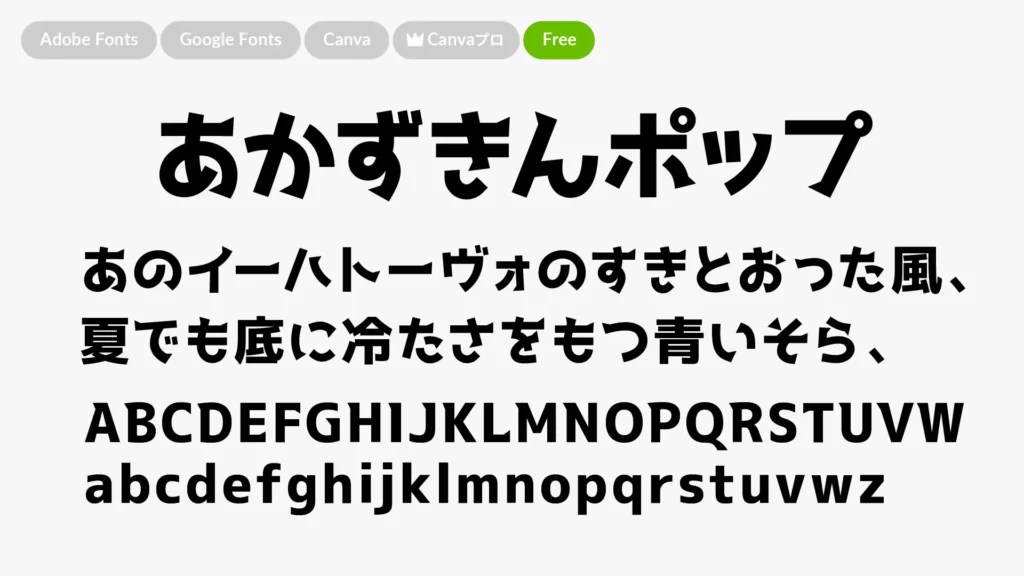
- はねたような先端が特徴の元気でポップなフォント
- 太さがあるのでYoutubeサムネイルなどにも使える◎
ABキリギリス
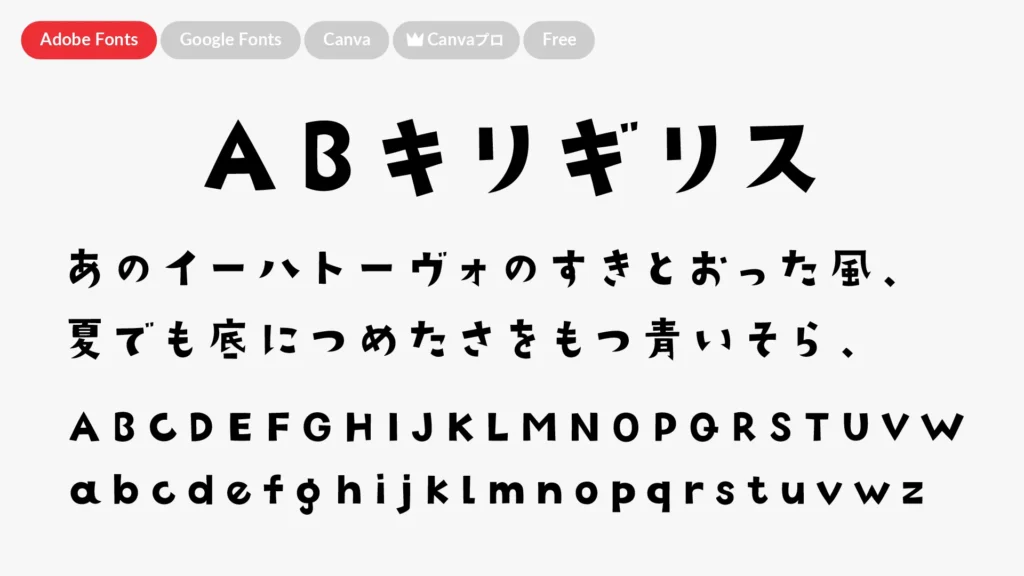
- コロっとしたちいさなフォント
- 切り絵みたいな手作り感溢れるフォルムがかわいい
ABとんぼ
- ちょっと縦に長めなのびのび楽しげな雰囲気をもつフォント
- 太さがあってポップなのでYoutubeサムネイルに使えそう
メガ丸
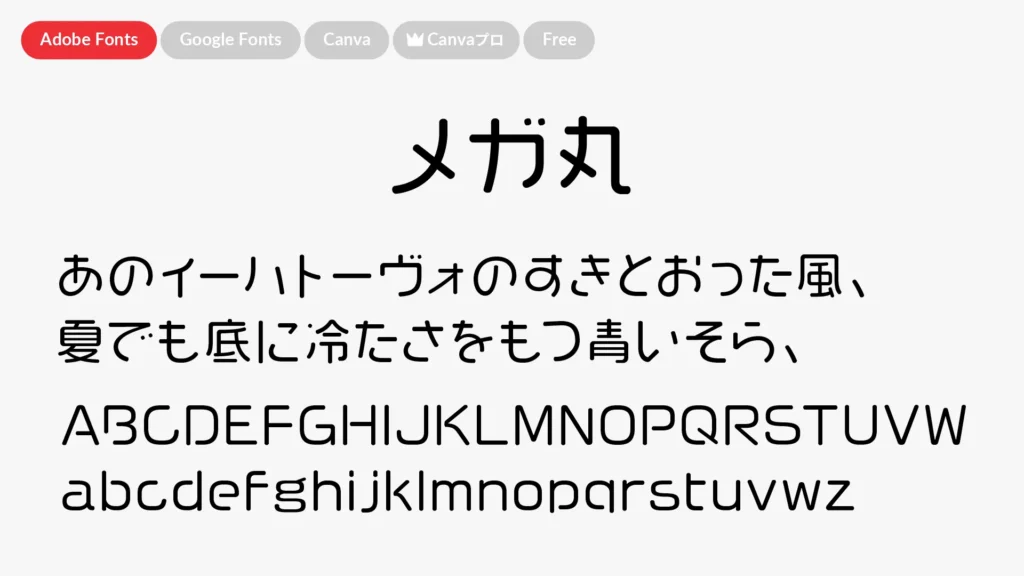
- 大胆な丸みをもつ個性的な丸ゴシック
- ユニークな漢字も多めに収録
バナナスリップ
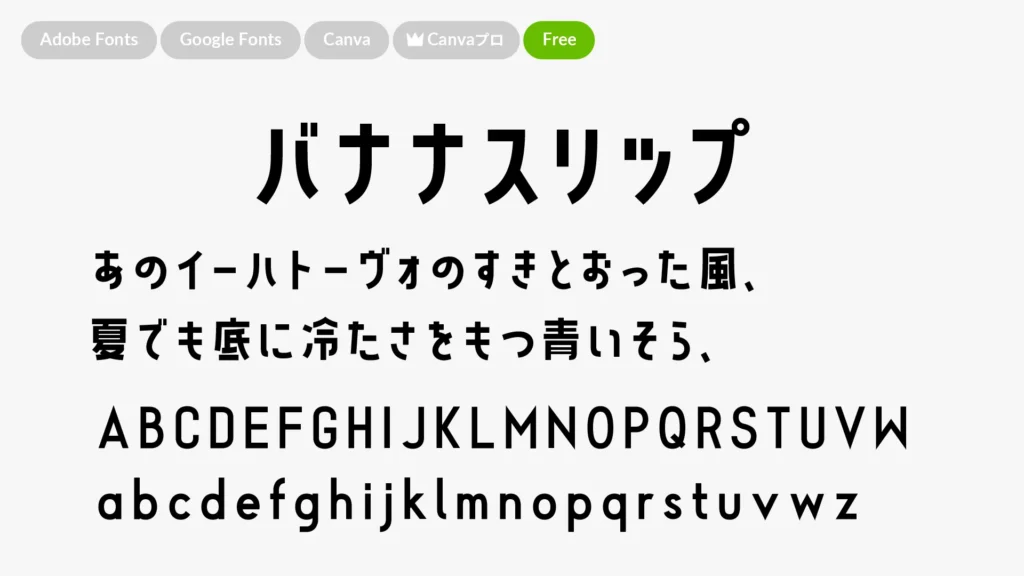
- 遊び心と活気に溢れたポップなフォント
- 全体的に縦長で太めなフォルム
せのびゴシック
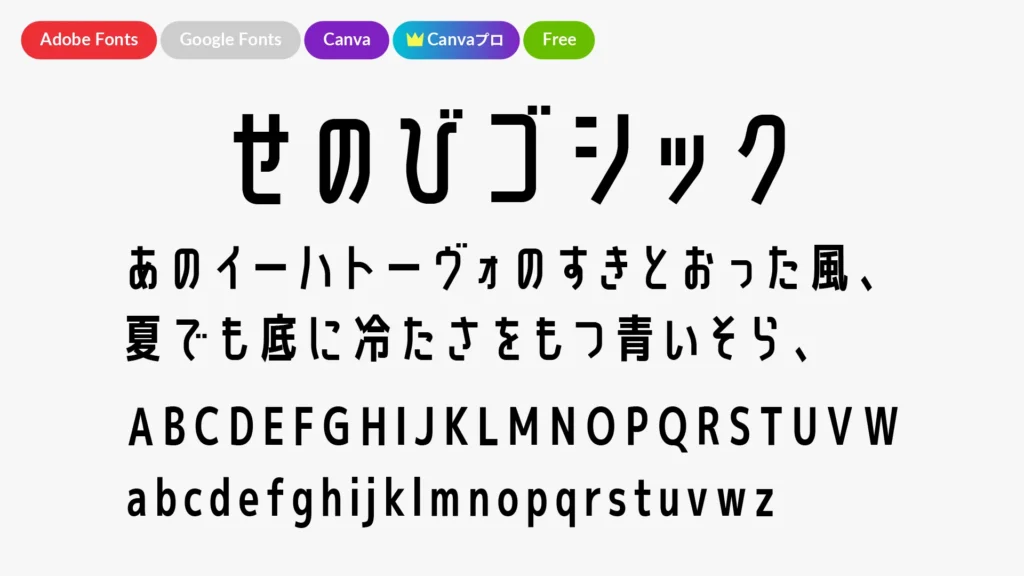
- こちらも縦に長めなフォント
- バナナスリップに比べるとちょっと細めでカクカク幾何学的なフォルム
ヨコスカブロック
- 収録はカタカナのみ
- ブロックのようにカクカクしたフォルム
デラゴシックワン
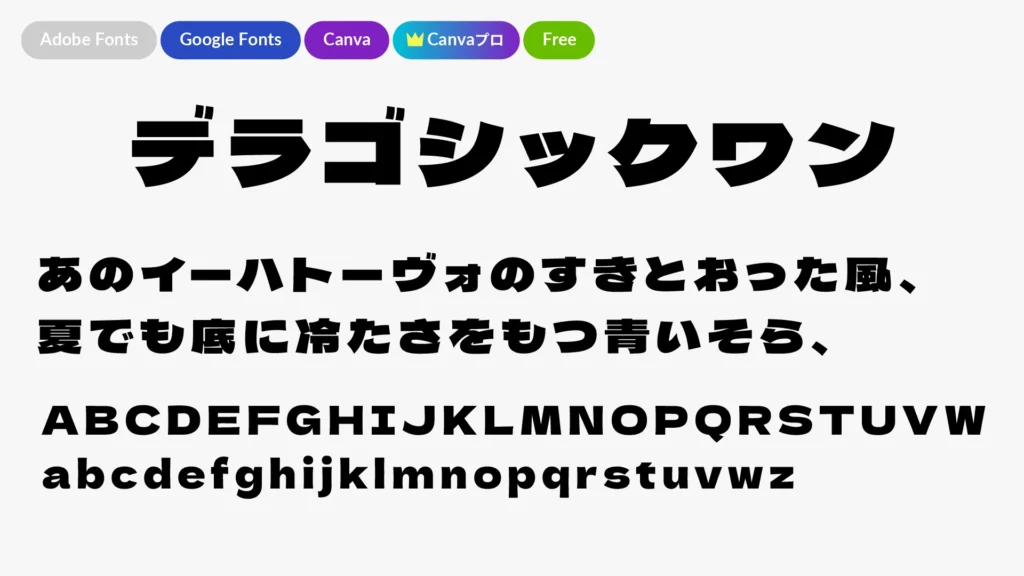
- 存在感強めな極太フォント
- サムネやアイキャッチに使うとインパクト抜群!
ロゴJrブラック
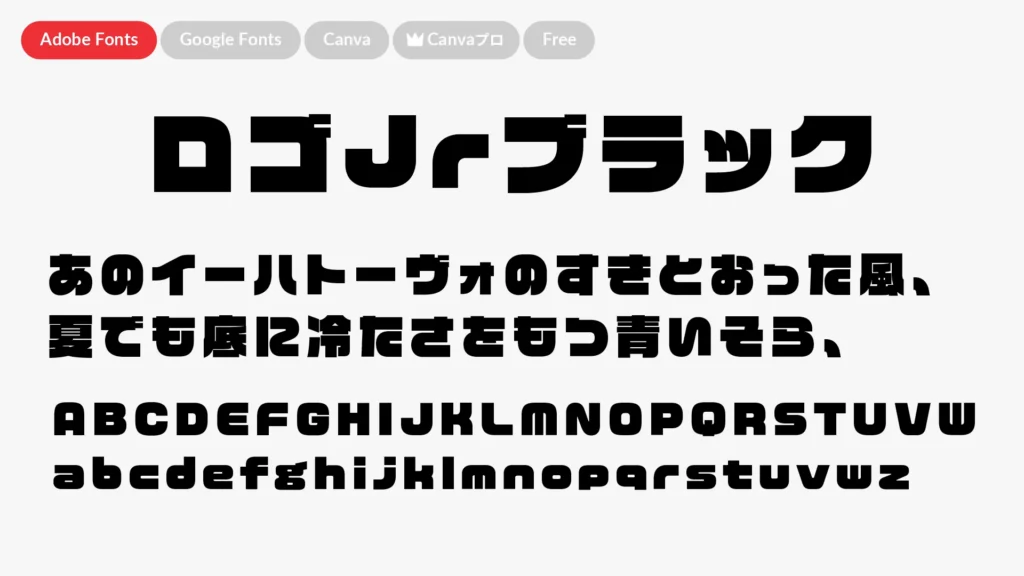
- こちらも極太で存在感強めなフォント
- ポップなフォルムでサムネイルにもロゴにも使える
ABカントリーロード
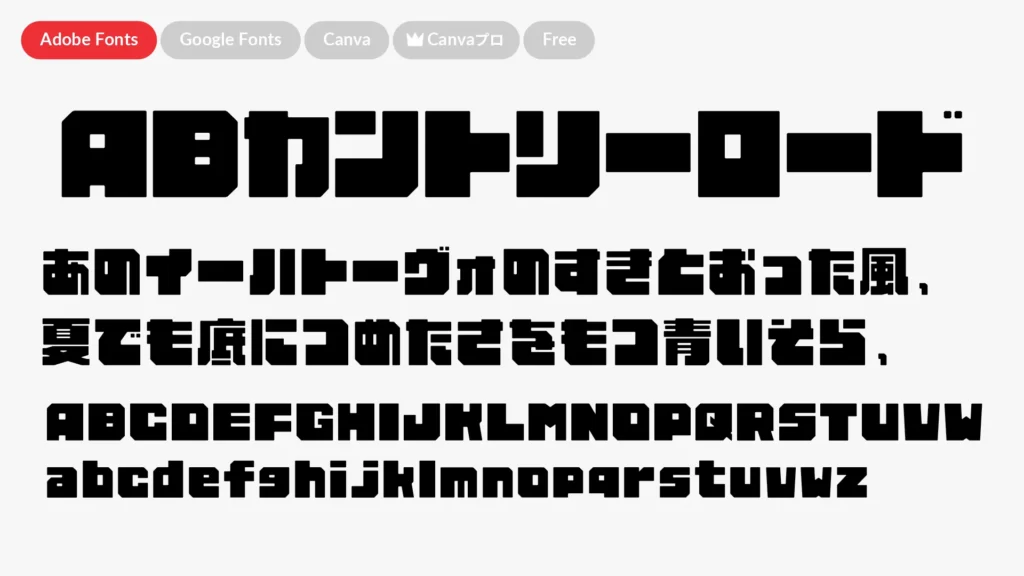
- 極太でカクカクしたコーナーをもつフォント
- 縦線と横線の太さのコントラストだったり下の重心が大きめだったりユニークなバランス
ABグー
- 極太な中に有機的な丸みもあるフォント
- インパクトは出したいけど柔らかさもほしいというときにピッタリ
カタカナボーイ
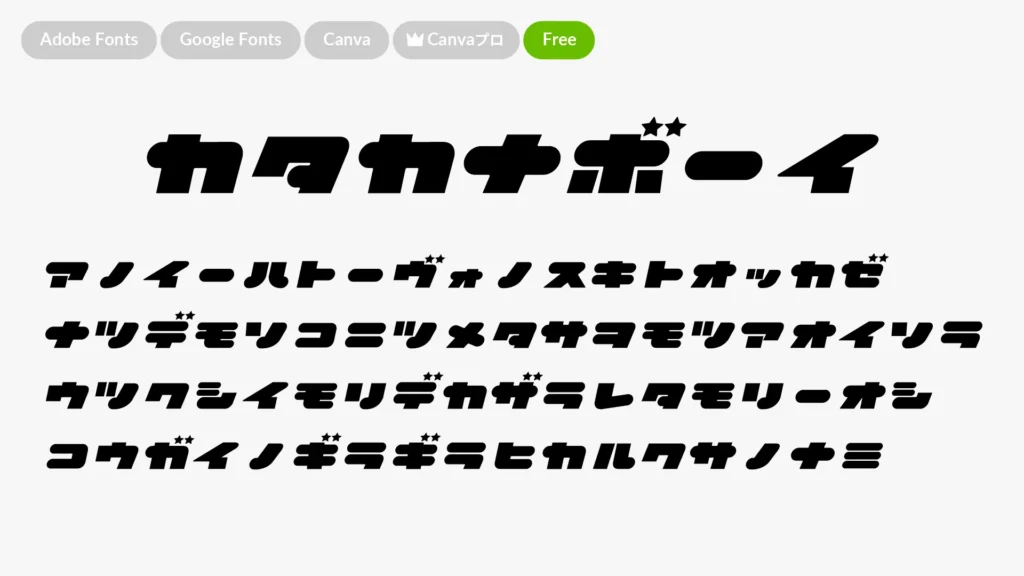
- カタカナのみ収録
- Y2Kっぽいレトロ感が特徴的
解星オプティ
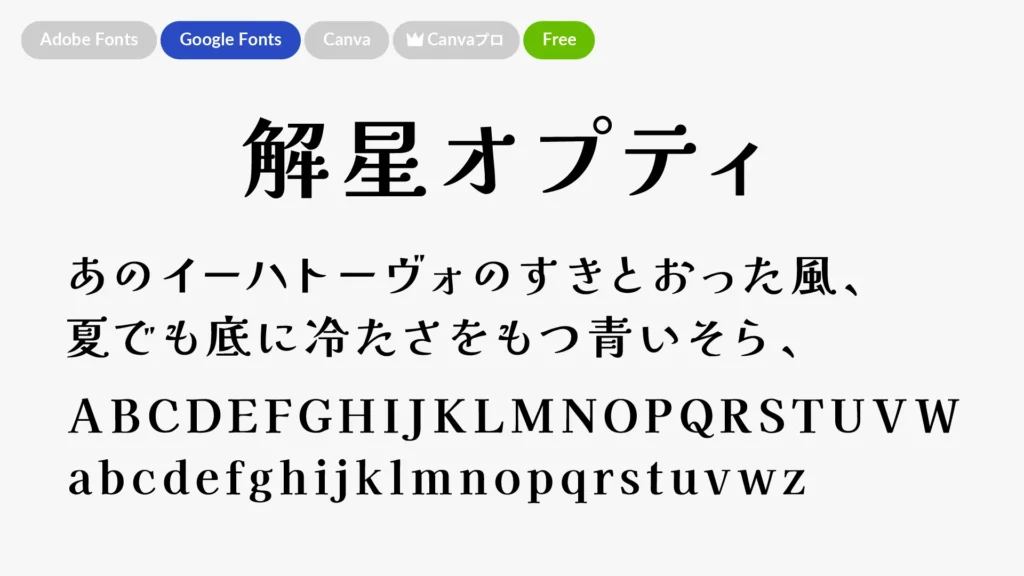
- 先端にクルンとした丸みをもつのが特徴
- 上品でありながらキュートな印象
ABこころ
- 本の表紙などでもよく見る優しいイメージのフォント
- Adobe Fontsでは太さは3段階使える(No1,No2,No3)
しろくまフォント
- 筆で書いたような手書き感強めなフォント
- あたたかさや優しさを出したいときにぴったり
クラフト明朝
- かわいくポップな明朝体に掠れた手書きっぽいニュアンスが加えられたフォント
- 名前の通り、クラフト感や手作りのあたたかさを出したいときに◎
AB丸花巻
- くずれたアンバランス感が絶妙にかわいいフォント
- キュートさ、ポップさを出したいときに◎
ABベイビーウォーク
- 赤ちゃんの動きから着想を得てつくられたフォント
- ところどころつながりきらない線が抜け感あってキュート